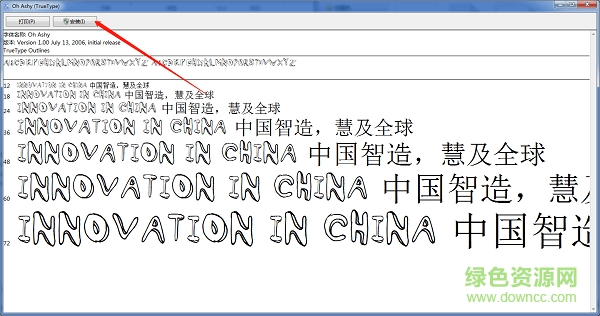
oh ashy手绘卡通3d立体字体
oh ashy手绘3d字体是一款类似于儿童话本上的字体,Q萌可爱的字体结构充满展现设计的童心,此款字体可用于多个字体标题,儿童作品设计中,喜欢就来绿色资源网下载吧!
oh ashy手绘卡通3d字体简介:
oh ashy手绘卡通3D立体字是一款卡通手绘3d英文字体。它的造型千变,基本没有任何规律可言,但是它的总体特征非常的明显——手绘、卡通、立体、空心等,有需要这款字体的用户可以在本站免费下载!
oh ashy手绘卡通3D立体字预览:
oh ashy手绘卡通3d立体字体